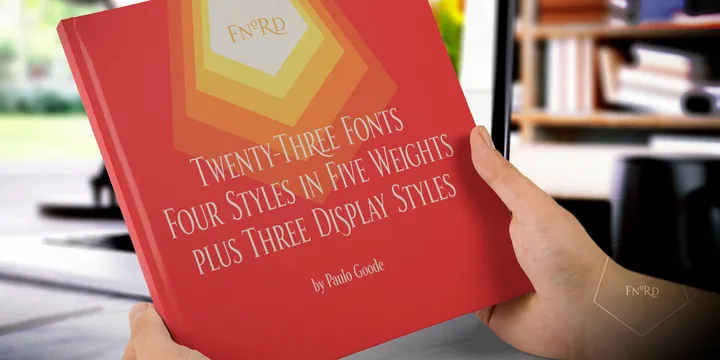
Introduzimos a nova família de fuentes. Introduzimos a Fnord Font Family . A Fnord é uma foz tipográfica serif humanista contemporânea, projetada para fins de visualização, títulos e texto de capa. É idealmente adaptada para múltiplas aplicações, contendo um total de 23 fontes – duas delas totalmente gratuitas. Cada fonte oferece traços ligações dispendiais, alternativas de swash e círculos menores reais. O design geral é limpo e simples, com uma pequena dose de rebeldia para preencher o desafio – a Fnord não se encaixa ao tradicional blueprint serif. A família foi projetada por Paulo Goode para ser extremamente versátil. Com um conjunto tão extenso, a Fnord Font Family está equipada com os recursos necessários para moldar qualquer projeto gráfico de acordo com suas necessidades. Não apenas isso, mas a foz também oferece uma graça única, o que a torna perfeita para design gráfico corporativo e identidade visual. A fonte pode ser encontrada em um vasto número de aplicativos e pode ser facilmente integrada à sua estratégia de marcação, criando uma presença forte e profissional.